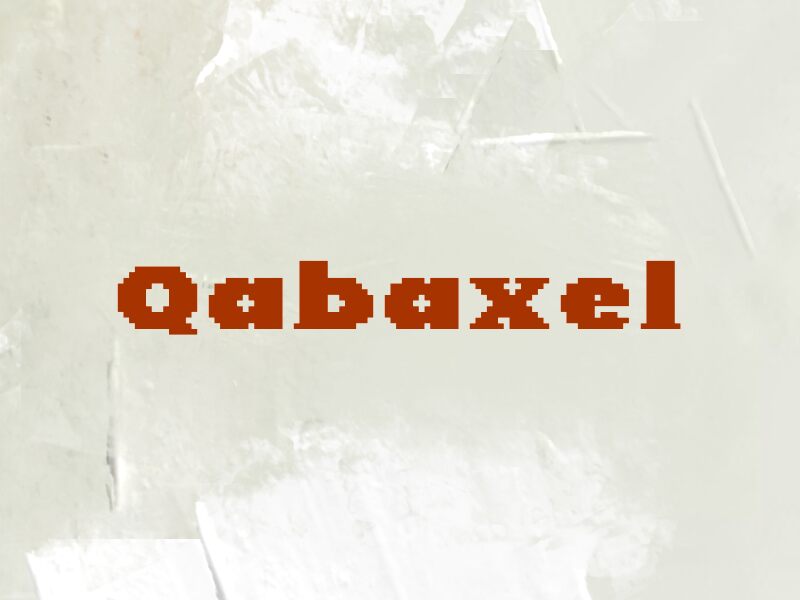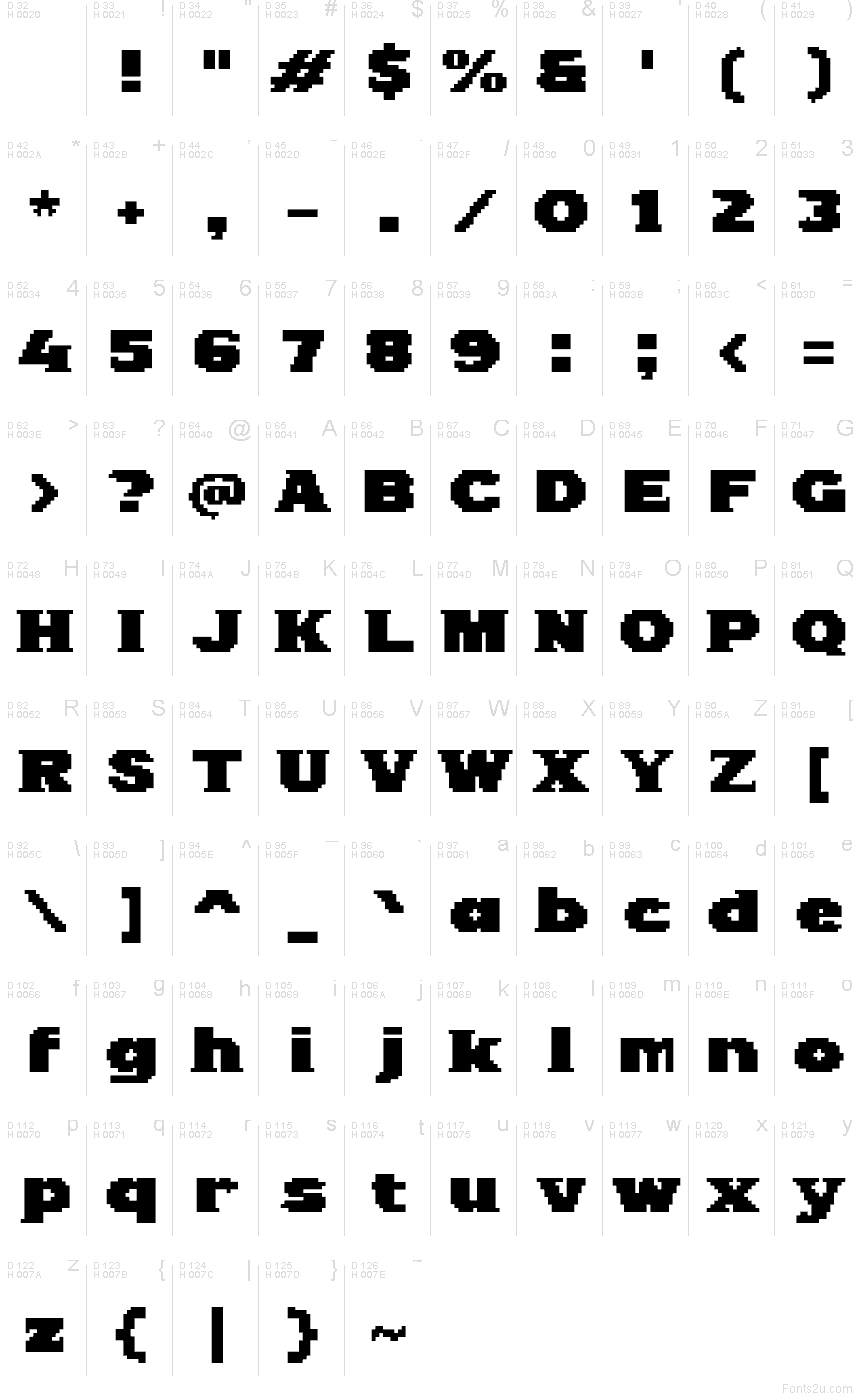
Qabaxel od Wep je bezplatné pixelové písmo typu display postavené z masivních čtvercových tvarů a ostře odstupňovaných okrajů. Jeho kompaktní písmena využívají blokovité výřezy a křížové otvory připomínající drobné herní symboly.
Tyto symbolické detaily se snadno doplňují s pixelovými postavičkami, ikonami rozhraní a dlaždicovým pozadím. Hodí se pro grafiku arkádových her, retro plakáty akcí a merchandising určený hráčům, kteří znají vizuální zkratku raných obrazovek. Jeho nejjasnějším uplatněním jsou titulkové nápisy s herní tématikou.
Qabaxel